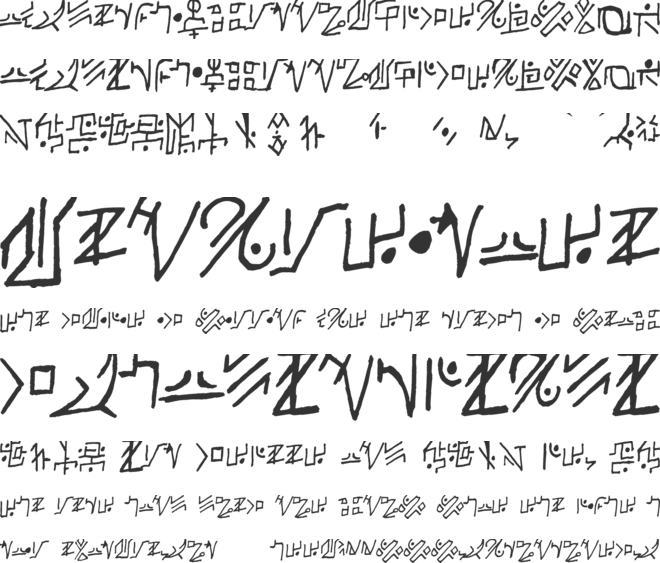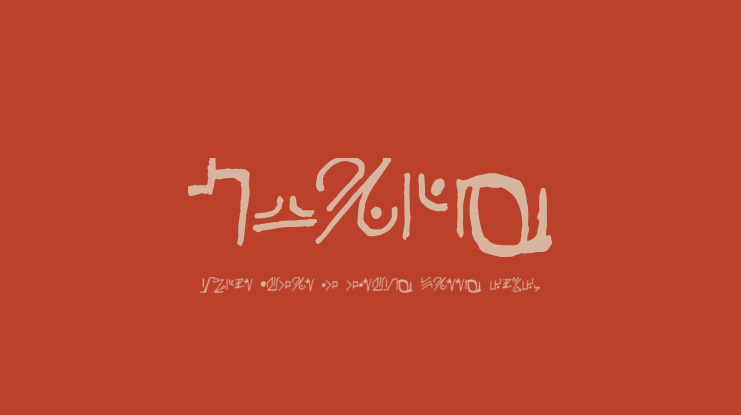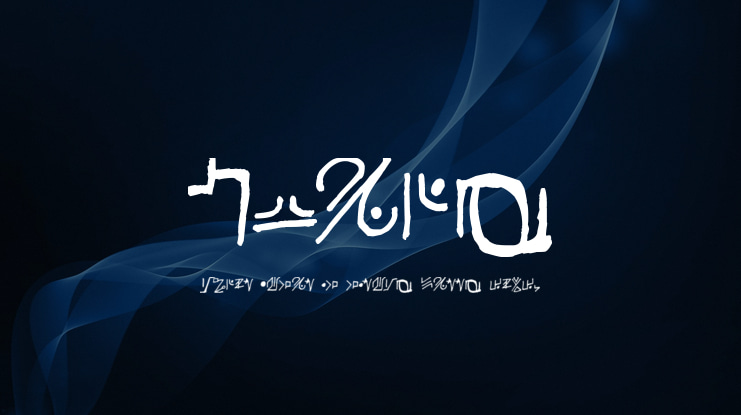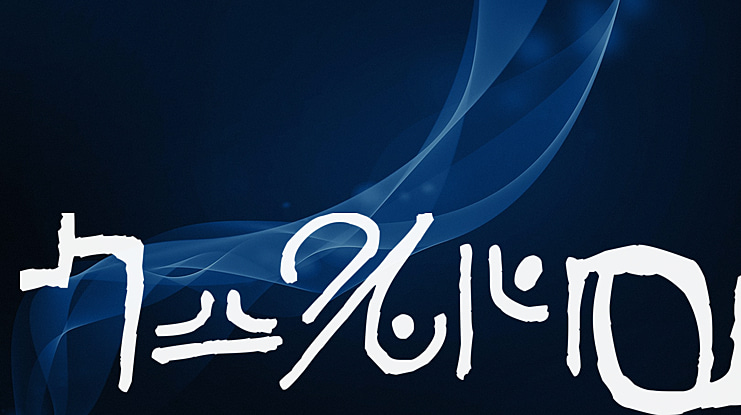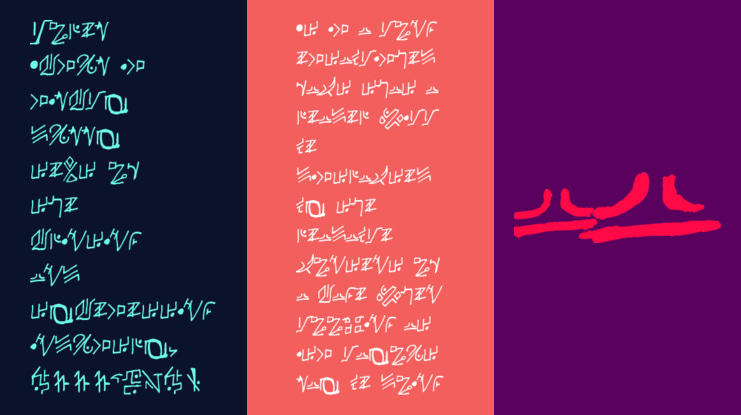
Haury Font
Essa fonte foi criada com um propósito de complementar um projeto pessoal.
Trata-se de uma linguagem "única" provinda de uma raça alienígena que fazem parte do universo Wanadi.
Wanadi é um projeto que visa criar história em quadrinho/animação que está aos poucos caminhando para o seu lançamento. Estamos apenas no início